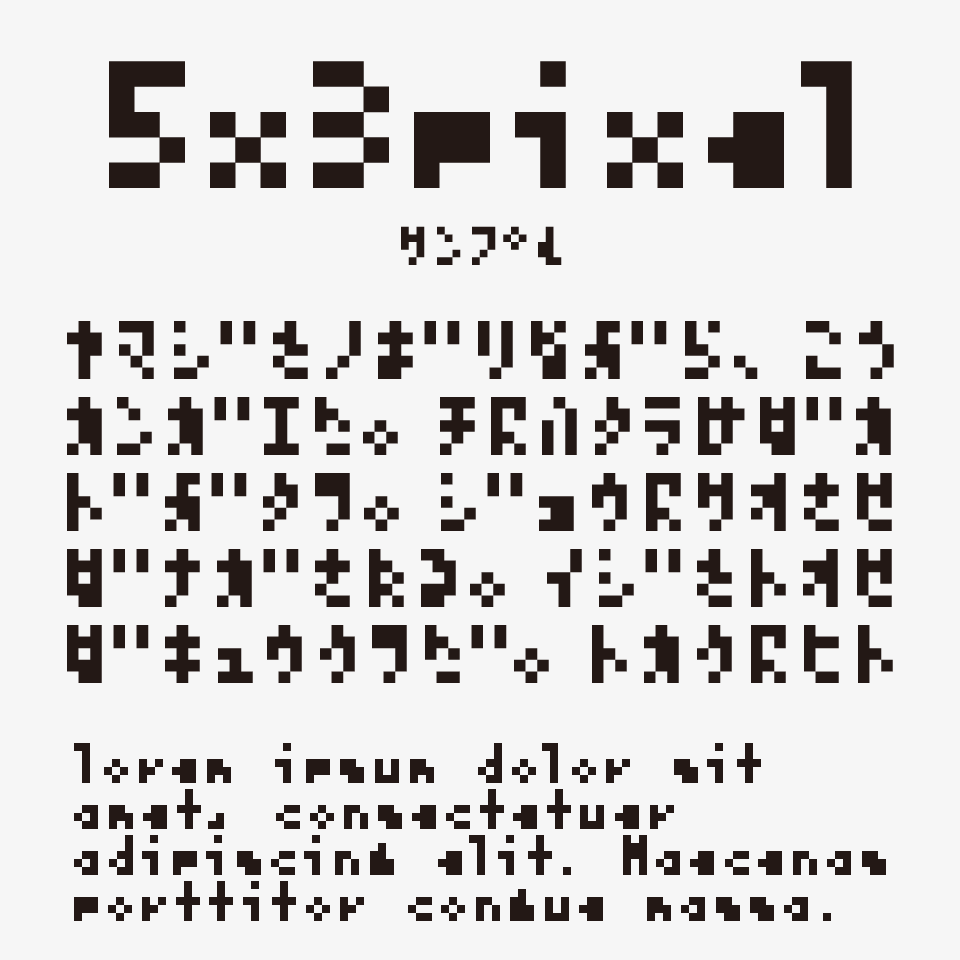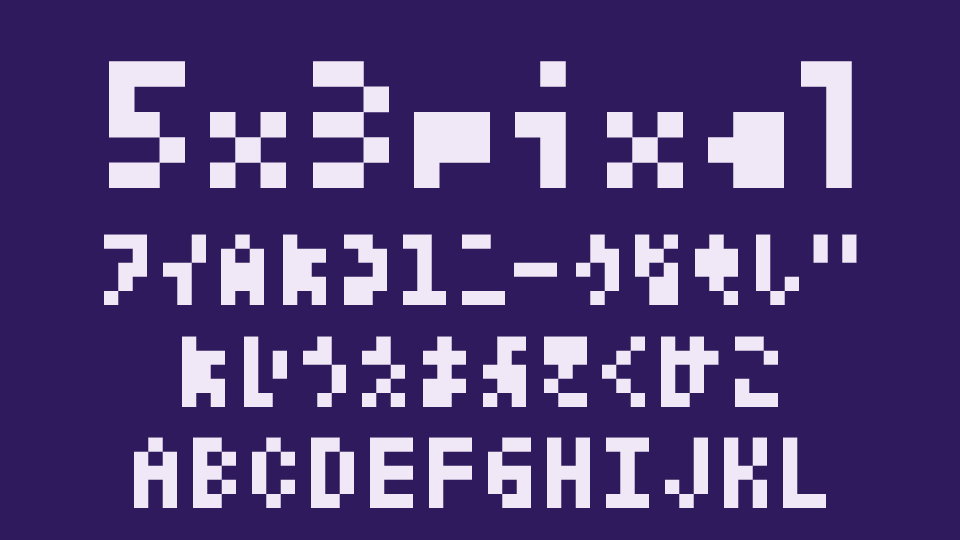
5x3pixelフォントは、その名の通り横5×縦3のドットグリッドという極限まで削ぎ落とされた制約の中で設計されたピクセルフォントです。
横5×縦3のドットグリッドというミニマルな構造の中でも、しっかりと判読性があるユニークなドットフォントです。
レトロゲームのUIやチップチューン系のビジュアルはもちろん、ローファイな世界観を演出したいビジュアルにもぴったりなフォントです。